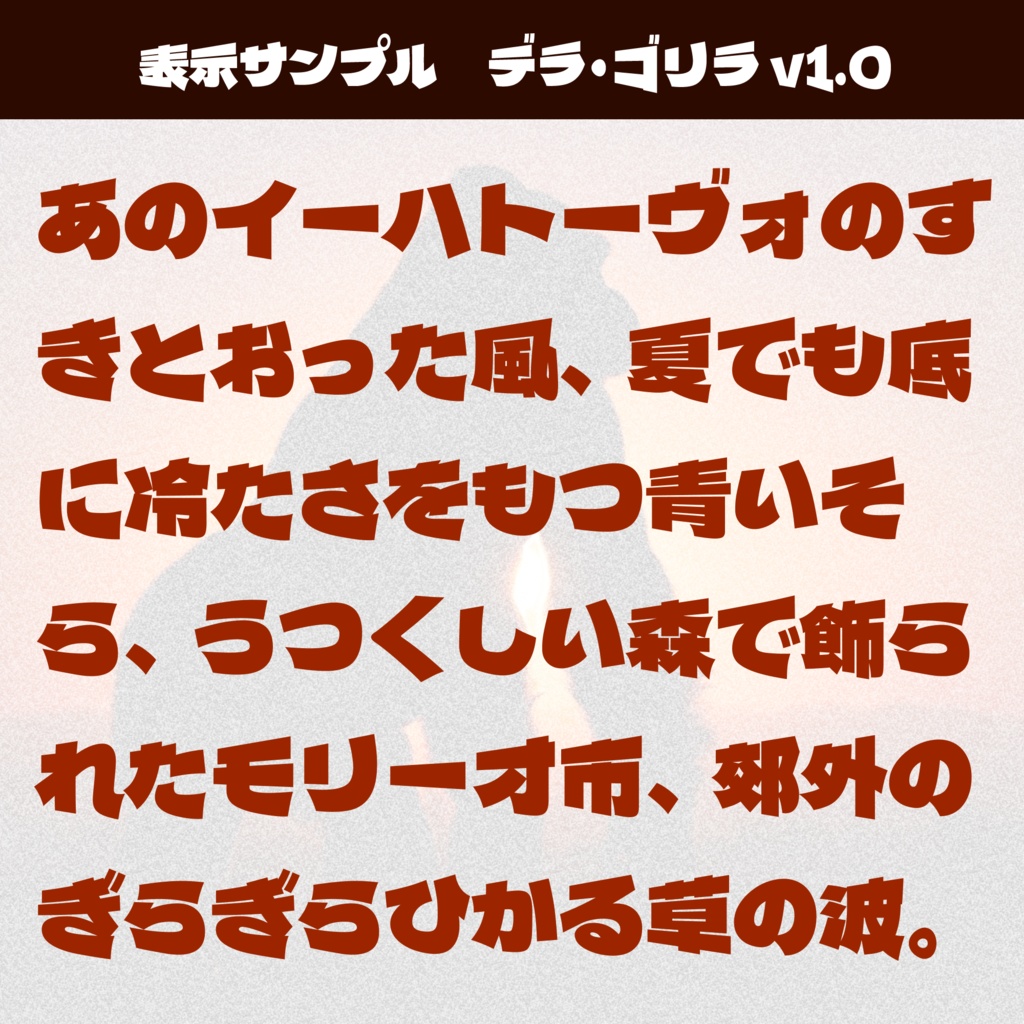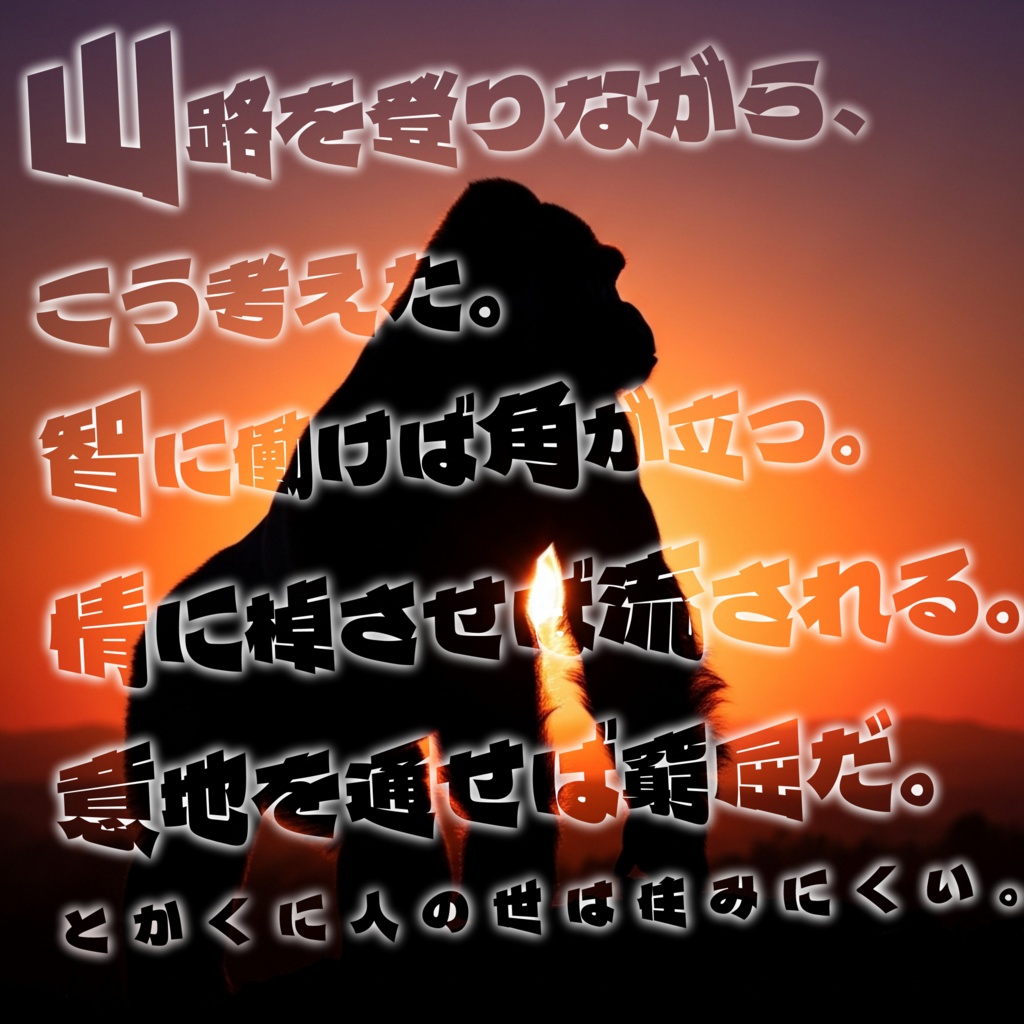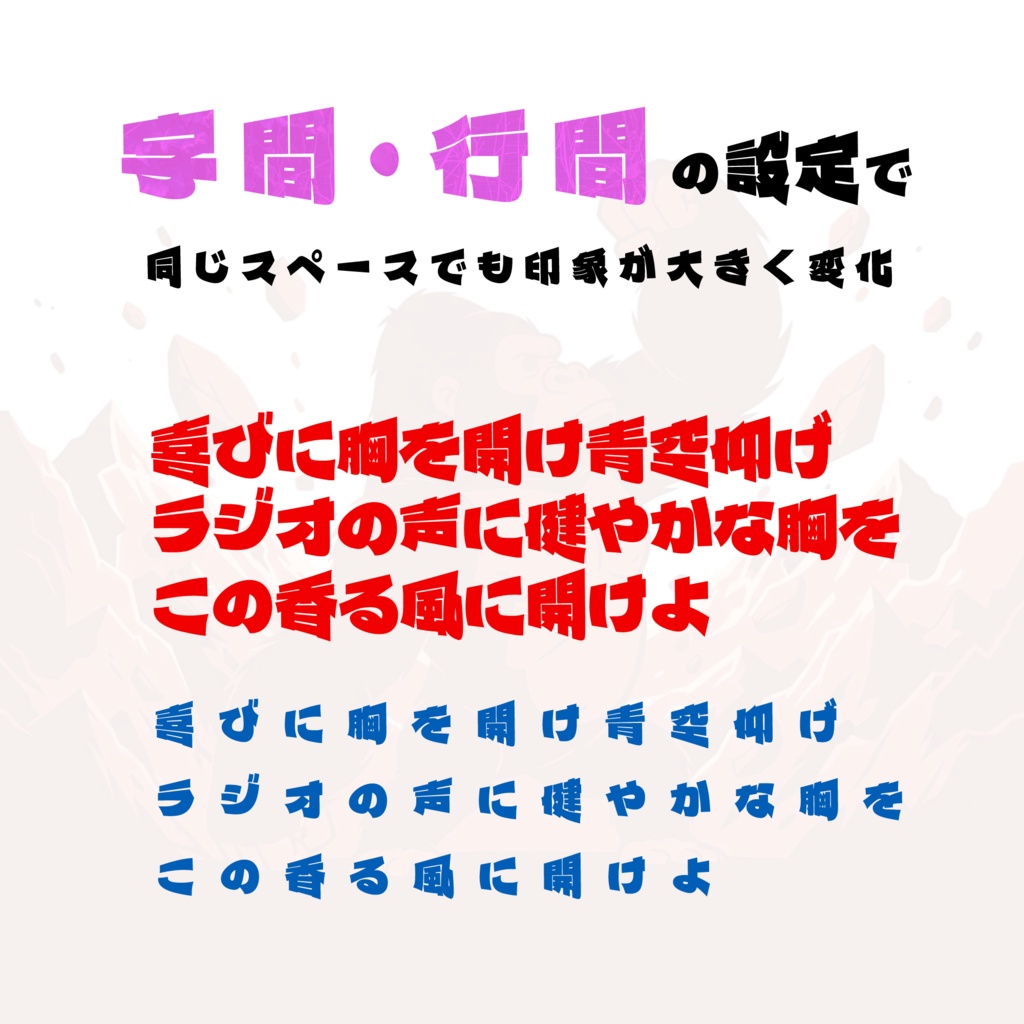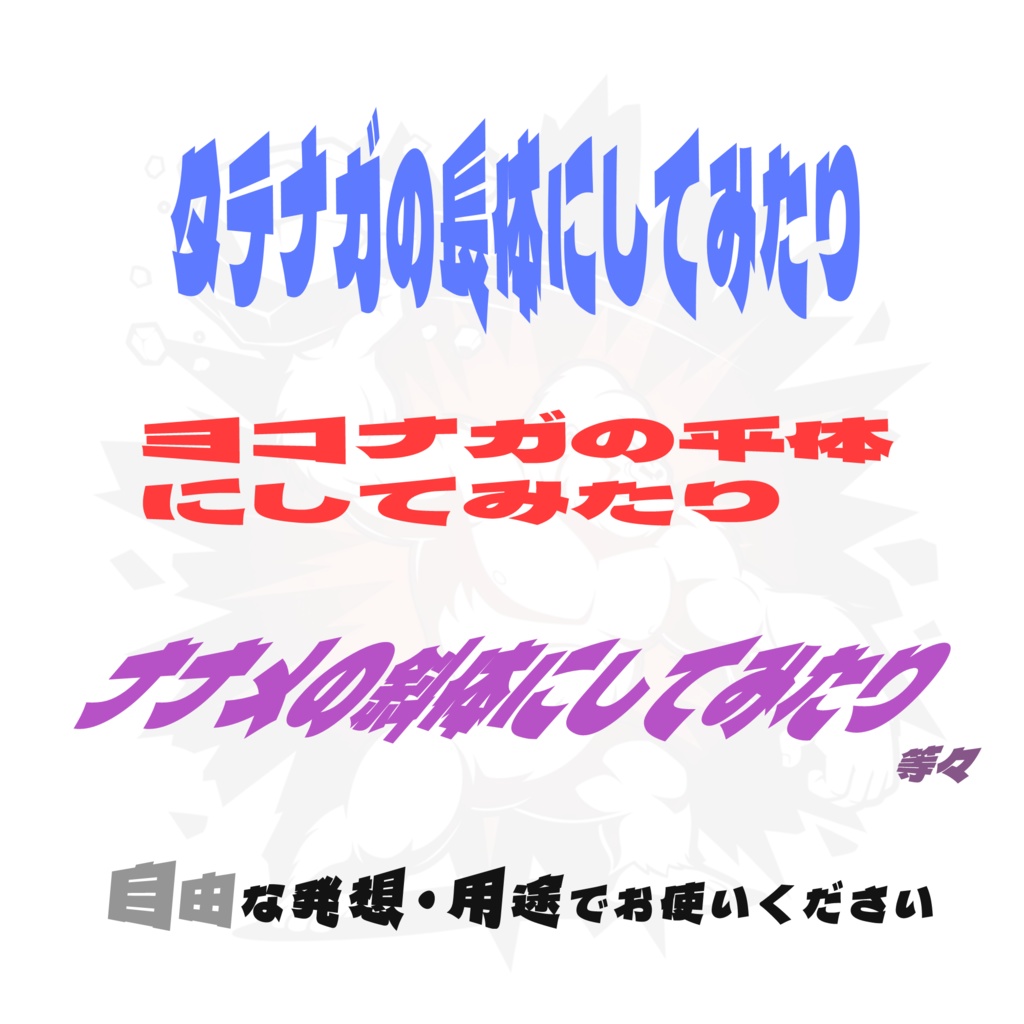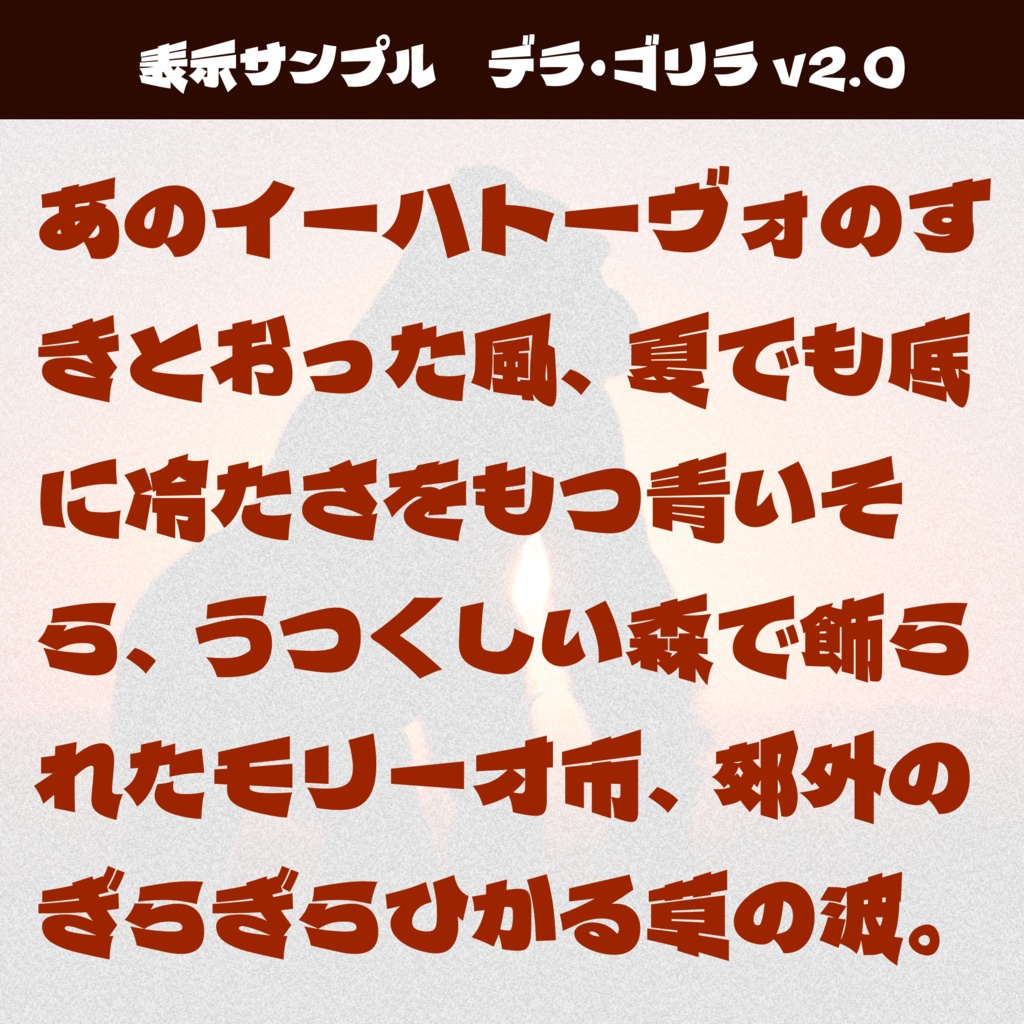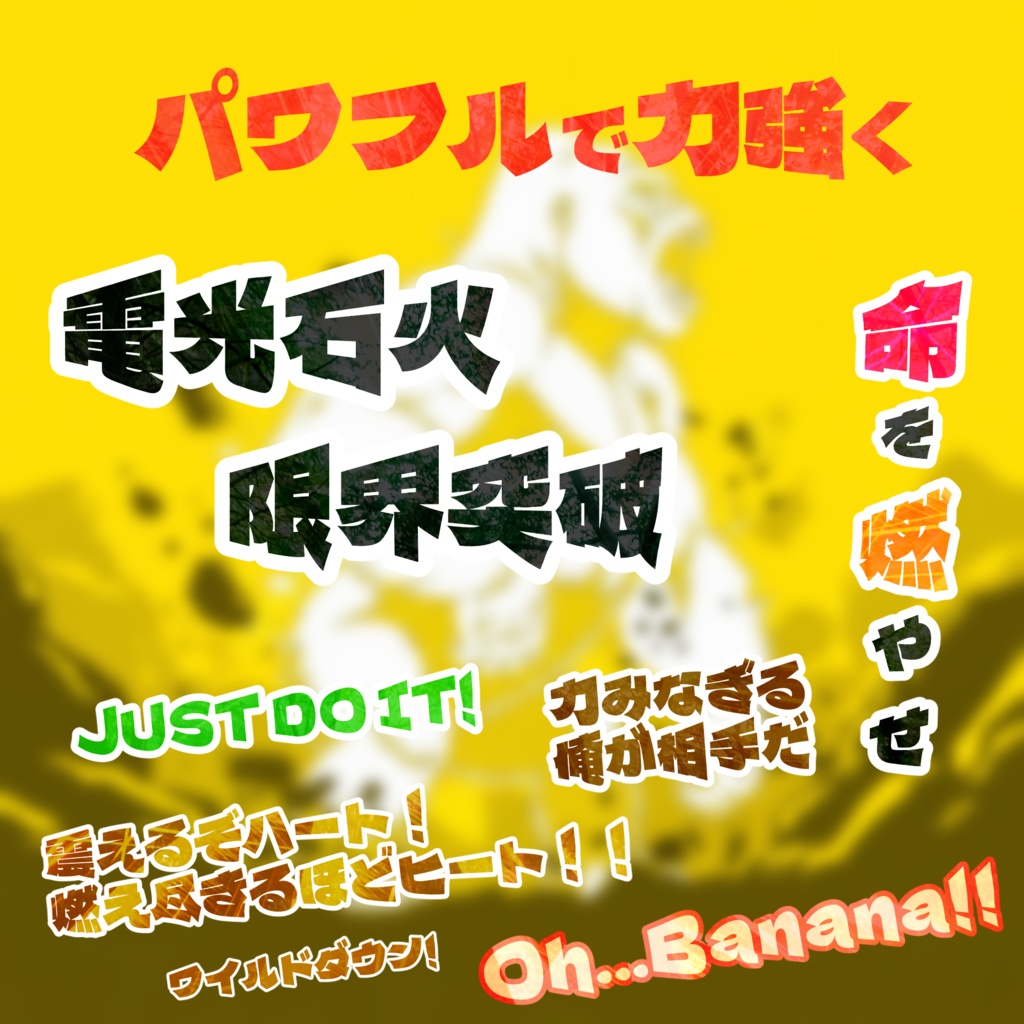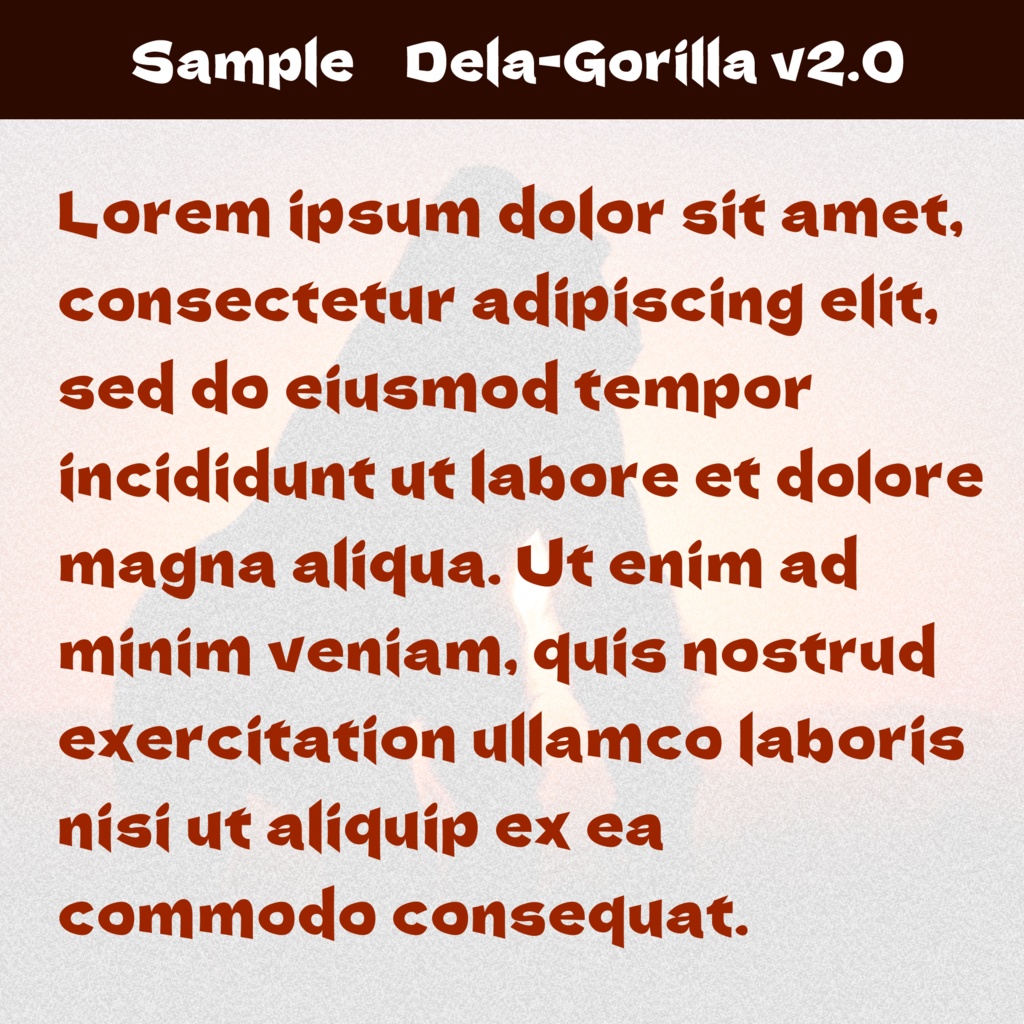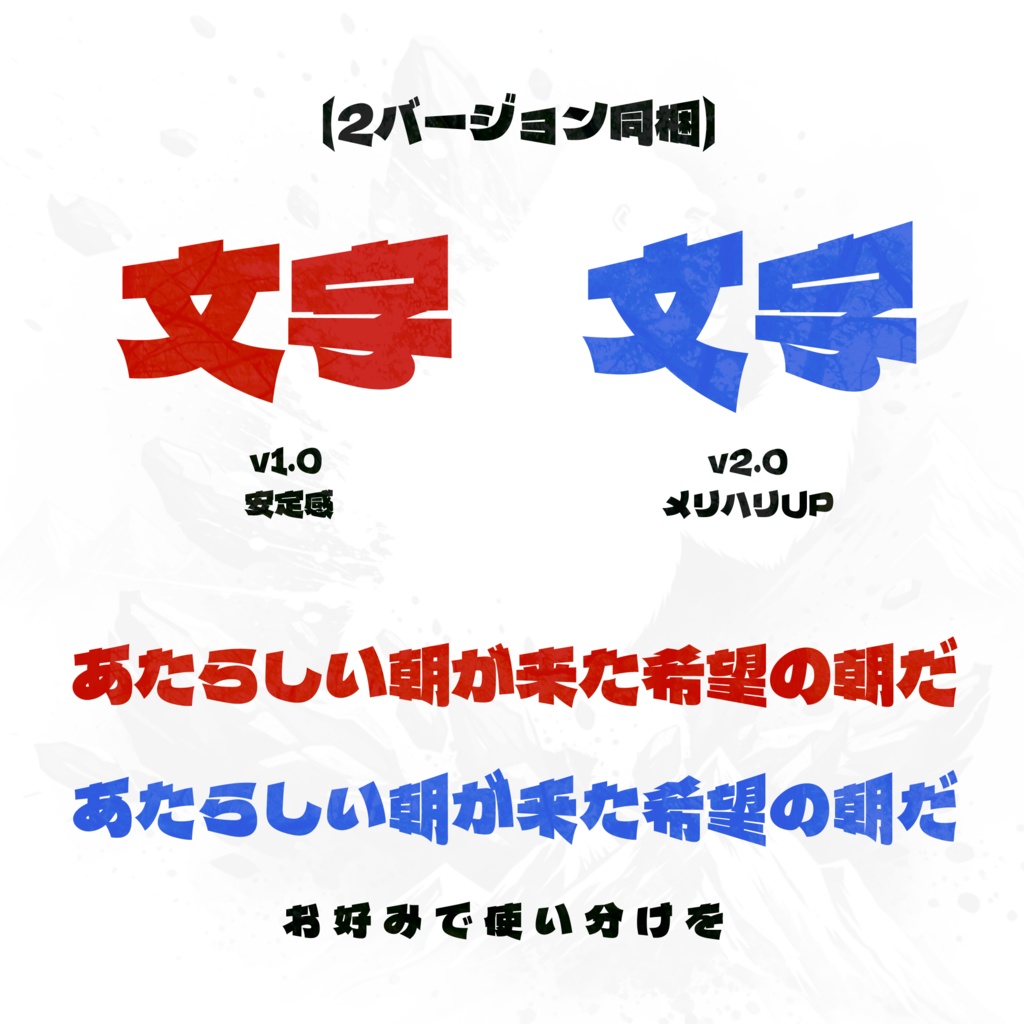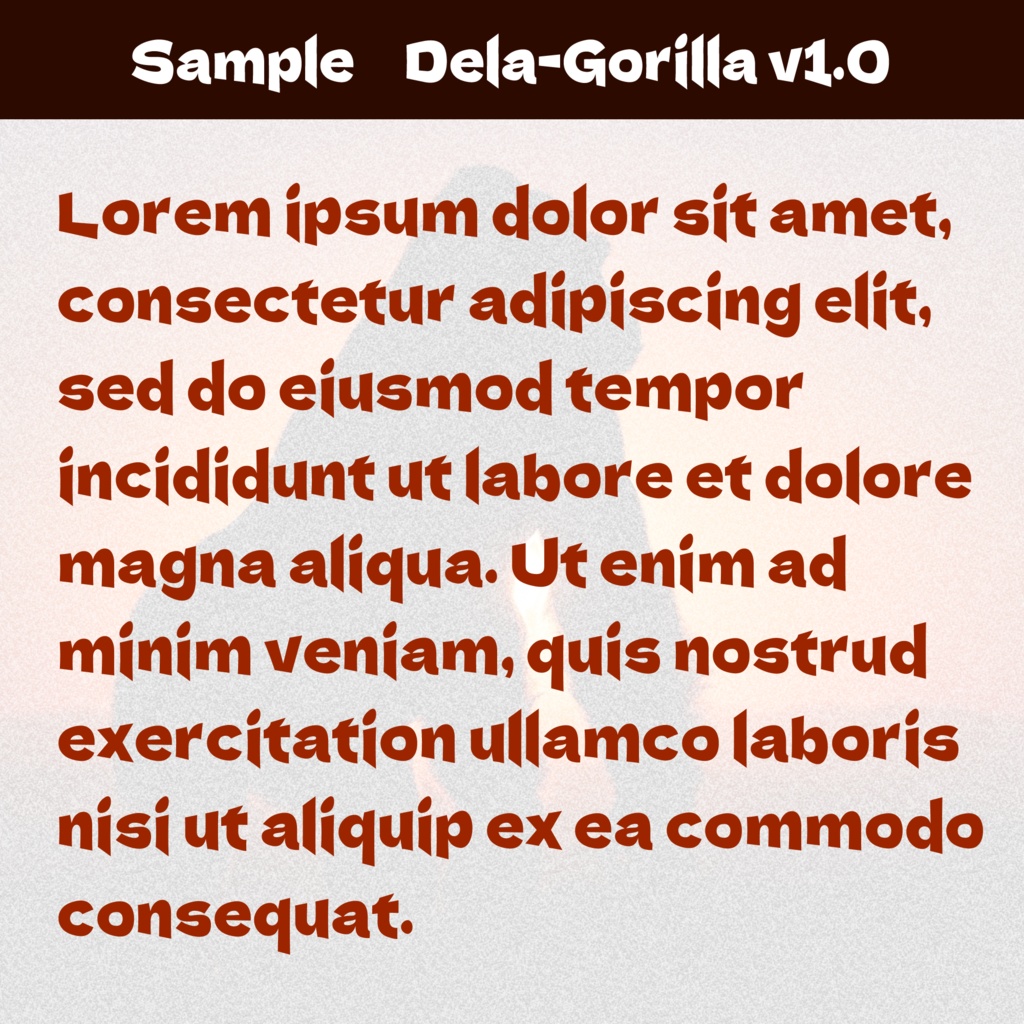
パワフル書体『デラ・ゴリラ』【フリーフォント】
「デラ・ゴリラ」(Dela-Gorilla) ゴリラのように力強い印象のフォントです。 当フォントは 「デラゴシック」(Dela Gothic One) https://github.com/syakuzen/DelaGothic を加工し作成しました。関係者の皆様に深くお礼申し上げます。
【デラ・ゴリラ v1.0】 元気でわんぱくなゴリラのようなフォントです。 自作のプログラムを用いて元フォントを一括加工した後、一部記号を手作業で調整して作成しました。 【デラ・ゴリラ v2.0】 知性が芽生え始めたゴリラのようなフォントです。 「v1.0」を元に、全体的な調整を行った結果メリハリがより強まりました。 また、漢字以外の多くの字形を手作業で調整し、可読性を高めました。